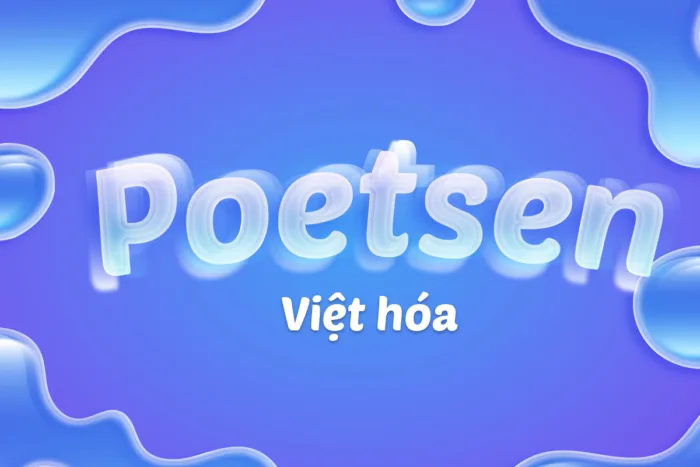
DVN PoetsenOne – Font chữ dày dặn, thân thiện và đầy cá tính
DVN – PoetsenOne Việt hóa là phiên bản Việt hóa của font PoetsenOne nổi bật trên Google Fonts, mang đến một phong cách đậm nét, bo tròn mềm mại và hiện đại. Với cấu trúc chữ cái chắc chắn và đầy đặn, font này truyền tải cảm giác thân thiện, dễ gần nhưng vẫn toát lên sự cá tính và nổi bật trong thiết kế.
PoetsenOne đặc biệt phù hợp cho các tiêu đề, poster, banner quảng cáo hoặc các dự án cần sự bắt mắt và thu hút ngay từ ánh nhìn đầu tiên. Phiên bản Việt hóa được chăm chút cẩn thận, giữ nguyên tinh thần vui tươi của bản gốc đồng thời hỗ trợ đầy đủ tiếng Việt với dấu và ký tự chuẩn. Đây là lựa chọn lý tưởng cho những nhà thiết kế đang tìm kiếm một font sans-serif tròn trịa, dễ đọc và có cá tính riêng biệt cho các dự án sáng tạo.